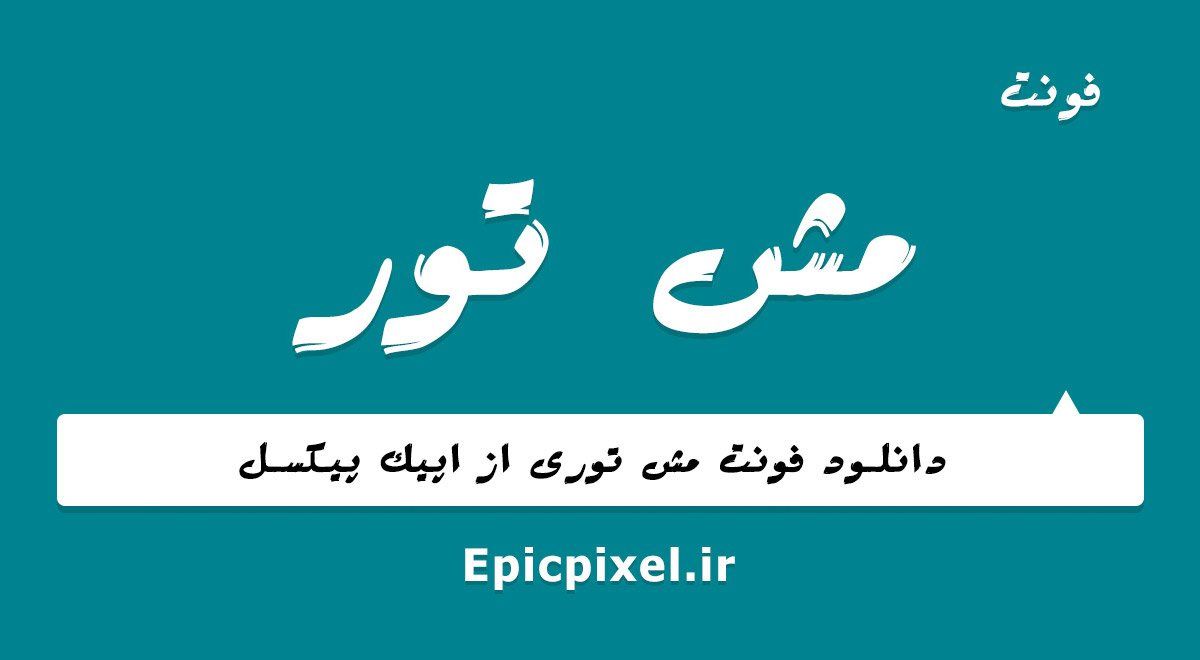
2 فونت مش تور فارسی
فونت فارسی مش تور، یک انتخاب عالی برای طراحانی است که به دنبال ظاهری فانتزی و در عین حال خوانا برای پروژه های خود هستند. این فونت با طراحی خاص خود، که ترکیبی از خطوط نرم و گوشه های گرد است، می تواند به نوشته های شما جلوه ای کودکانه، دوستانه و جذاب ببخشد.
طراحی باکیفیت و فانتزی این فونت، آن را به گزینه ای ایده آل برای انواع طراحی ها، به ویژه متون طولانی، تبدیل کرده است. خوانایی بالای این فونت حتی در اندازه های کوچک نیز حفظ می شود و چشم را خسته نمی کند. مهم تر از همه، این فونت کاملا رایگان برای دانلود است و شما می توانید بدون هیچ هزینه ای از آن در پروژه های شخصی و تجاری خود بهره ببرید. اگر به دنبال فونتی هستید که به طرح هایتان روحی تازه ببخشد و در عین حال استفاده از آن آسان و بدون دردسر باشد، فونت فارسی مش تور بهترین انتخاب برای شماست.